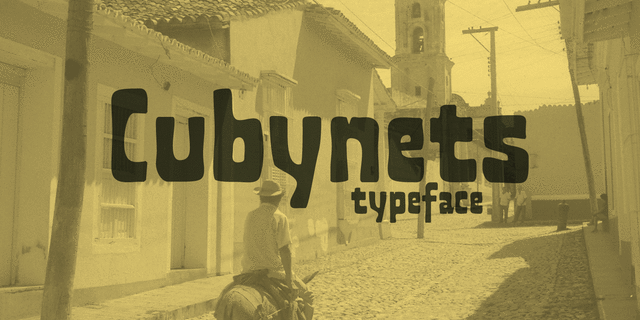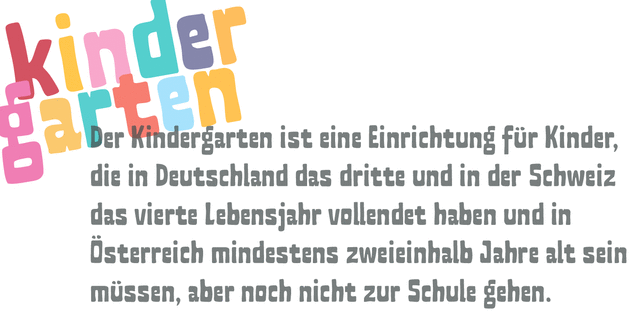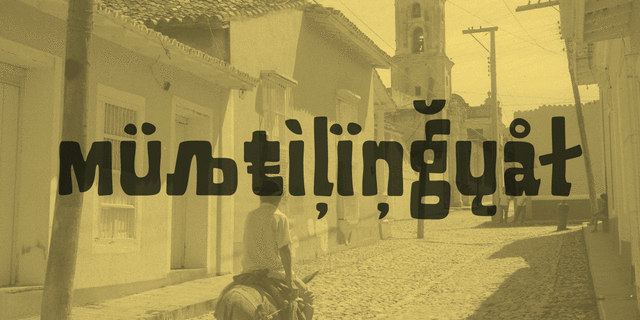
Шрифт Кибинец имеет грубоватый но добродушный характер. Идеально подходит для вывесок, упаковки и объявлений. Смотря на него хочется надеть шляпу и закурить сигару. Шрифт разработан Сергеем Ткаченко в 2014 году.
ковбойский, старомодный, ремесленный, фермерский, крафтовый, устойчивый, качественный, добротный, самостоятельный, западный, статичный, жаркий, суровый, знойный, громкий, деревянный, южный, мужественный, мачо, наивный, грубый, неотесанный, дружелюбный, забавный, прикольный, рукотворный, остроумный, квадратный, прямоугольный, веселый, тяжелый, заметный, броский, тесный, неряшливый, игривый, оригинальный, карикатурный, мультяшный, живой, характерный, неровный, праздный, гуляющий, горячий, огненный, бандитский, тропический, артизанальный, вернакулярный, кинематографичный